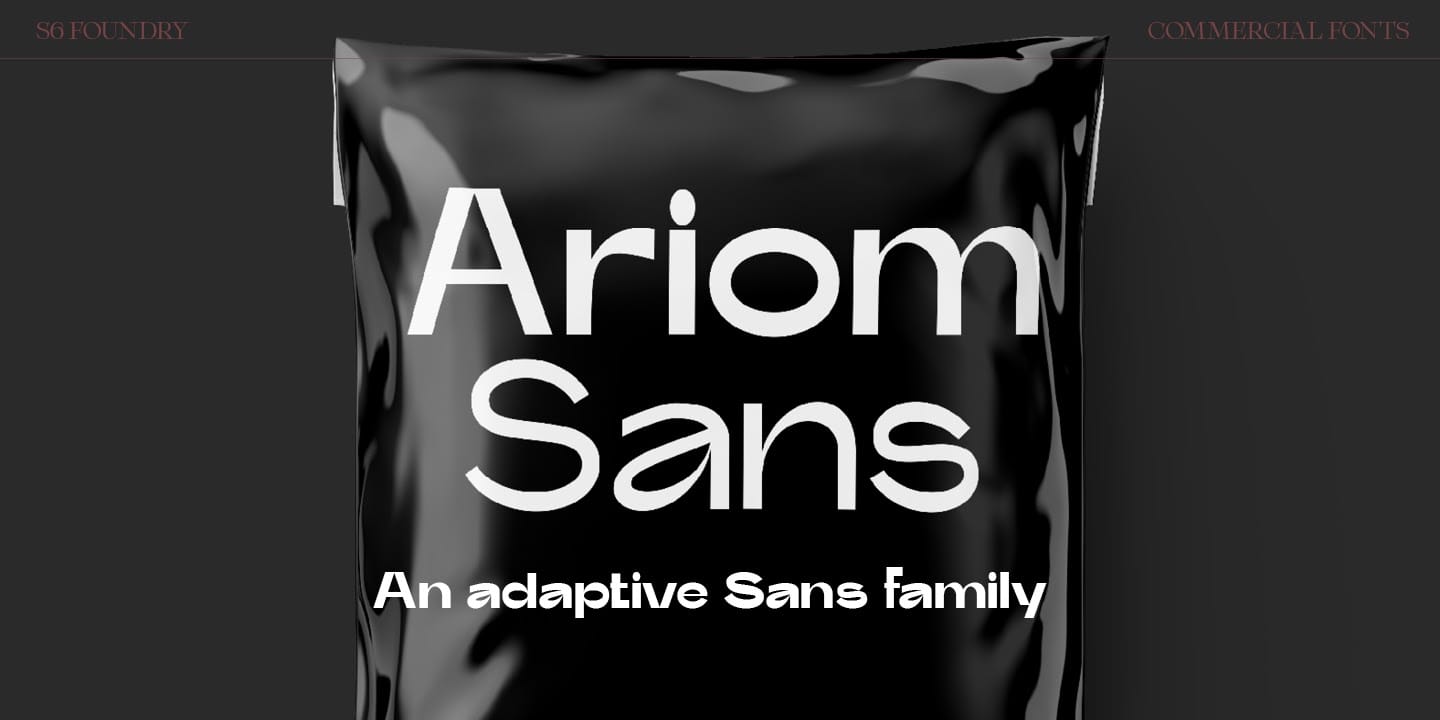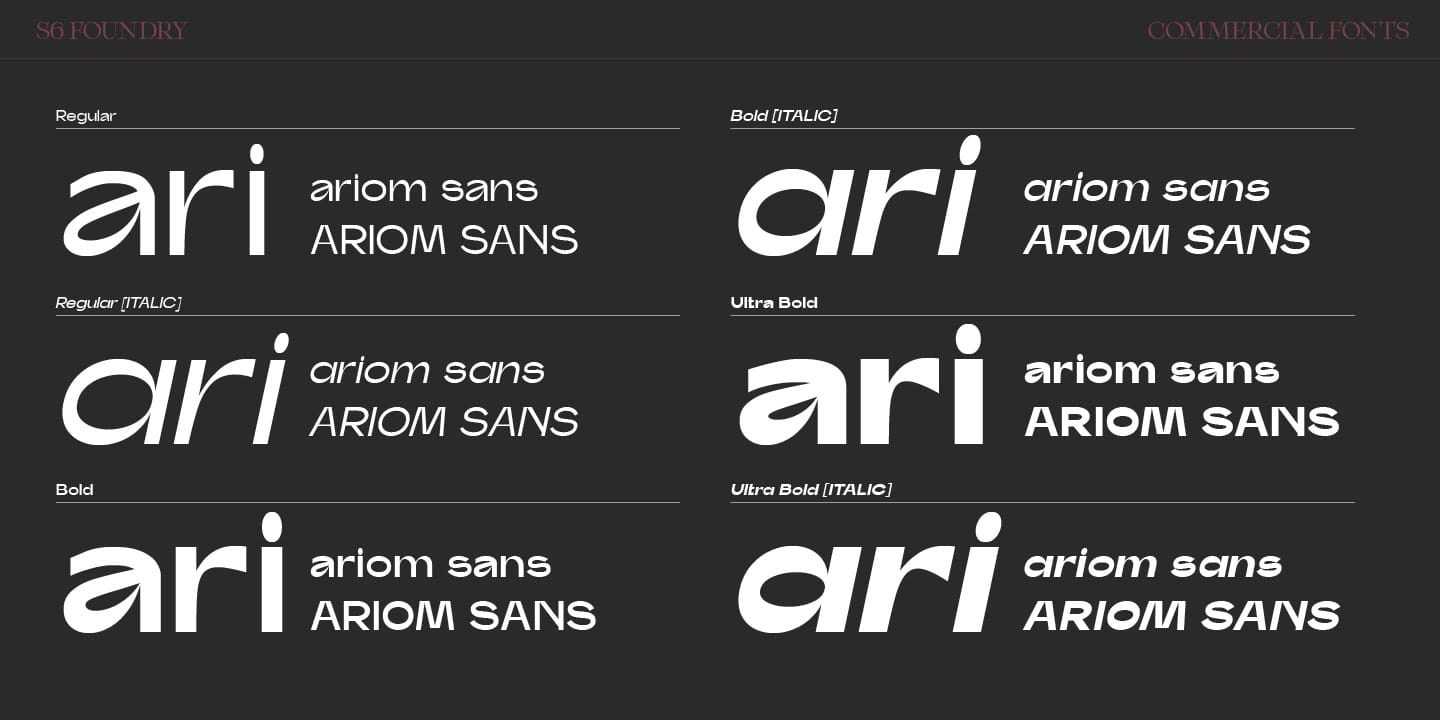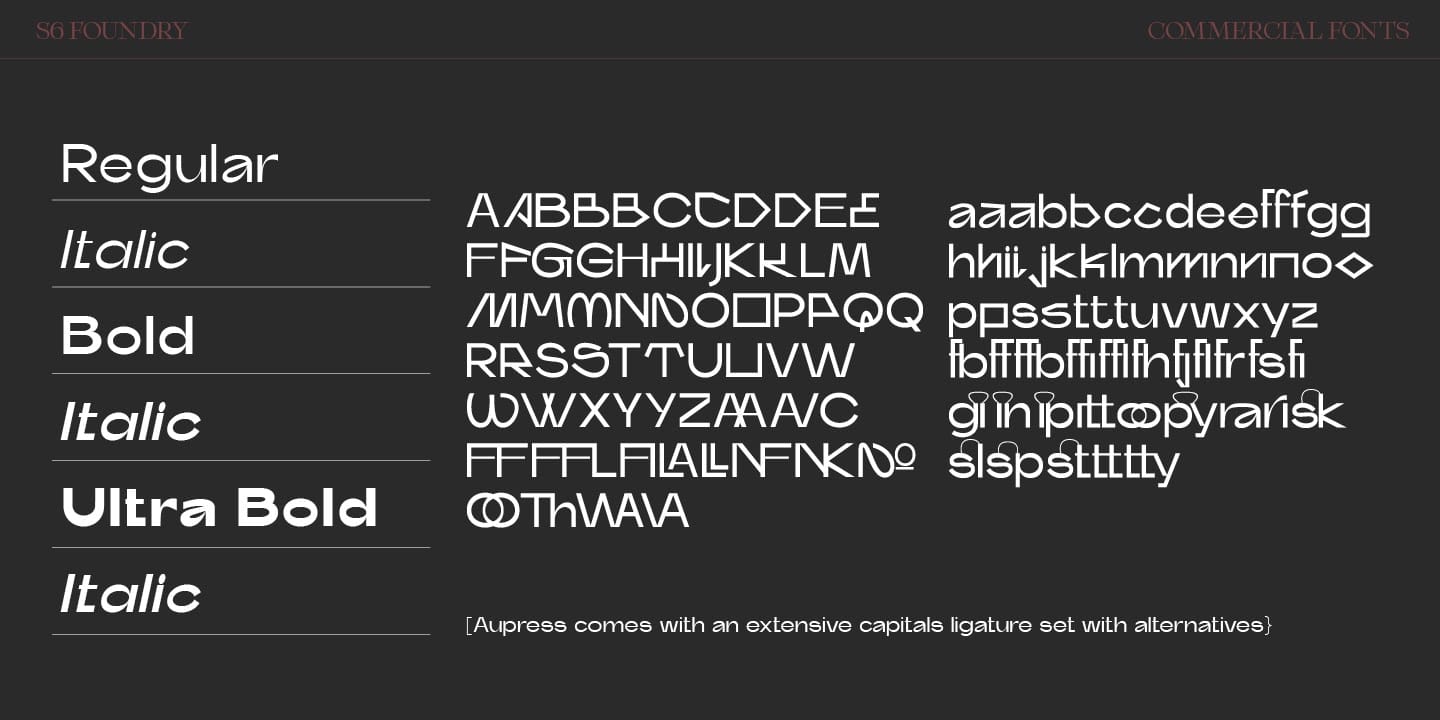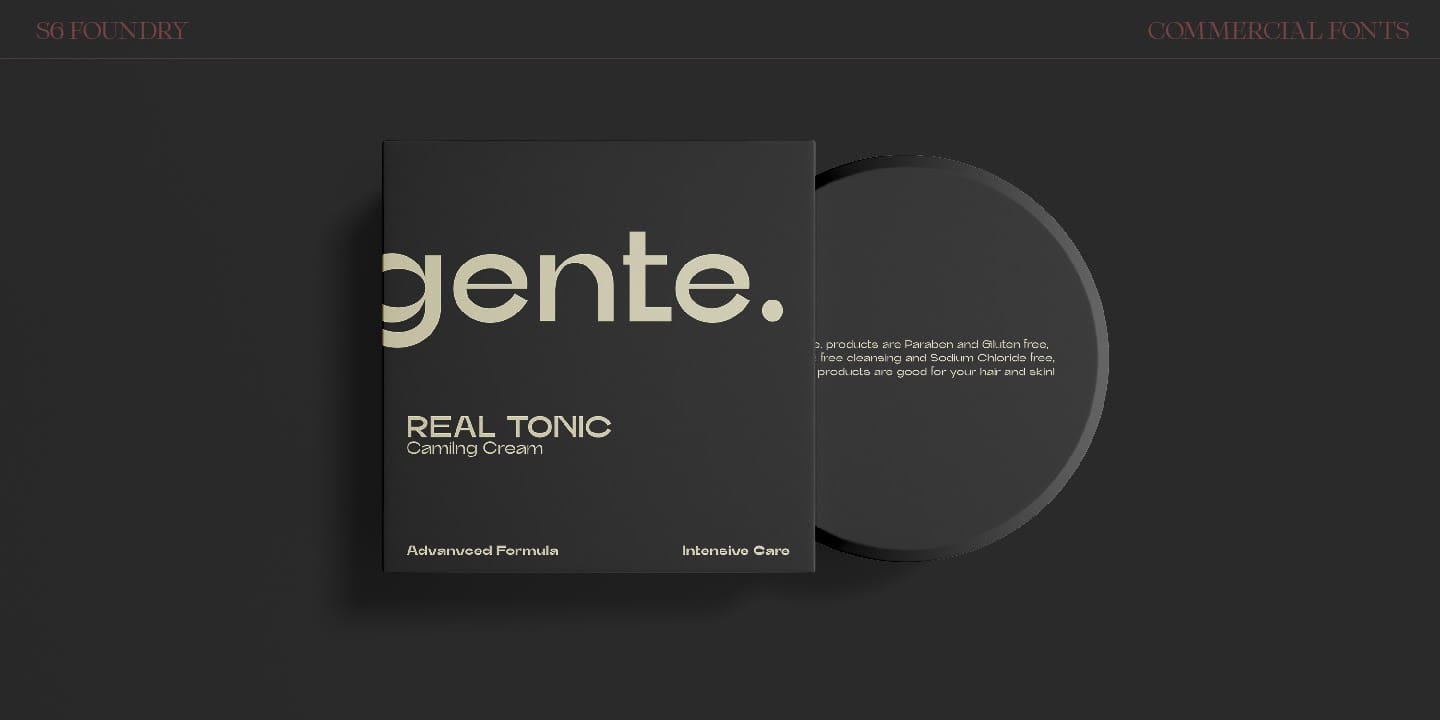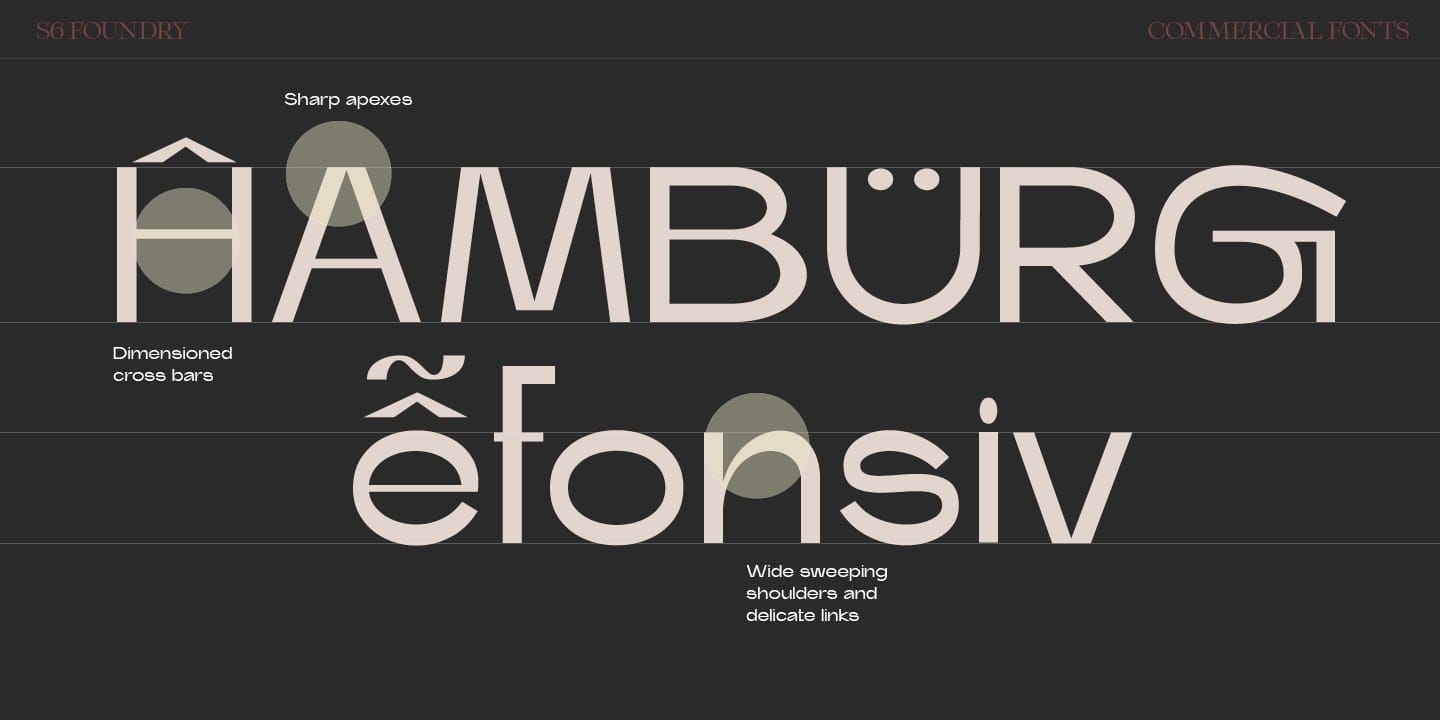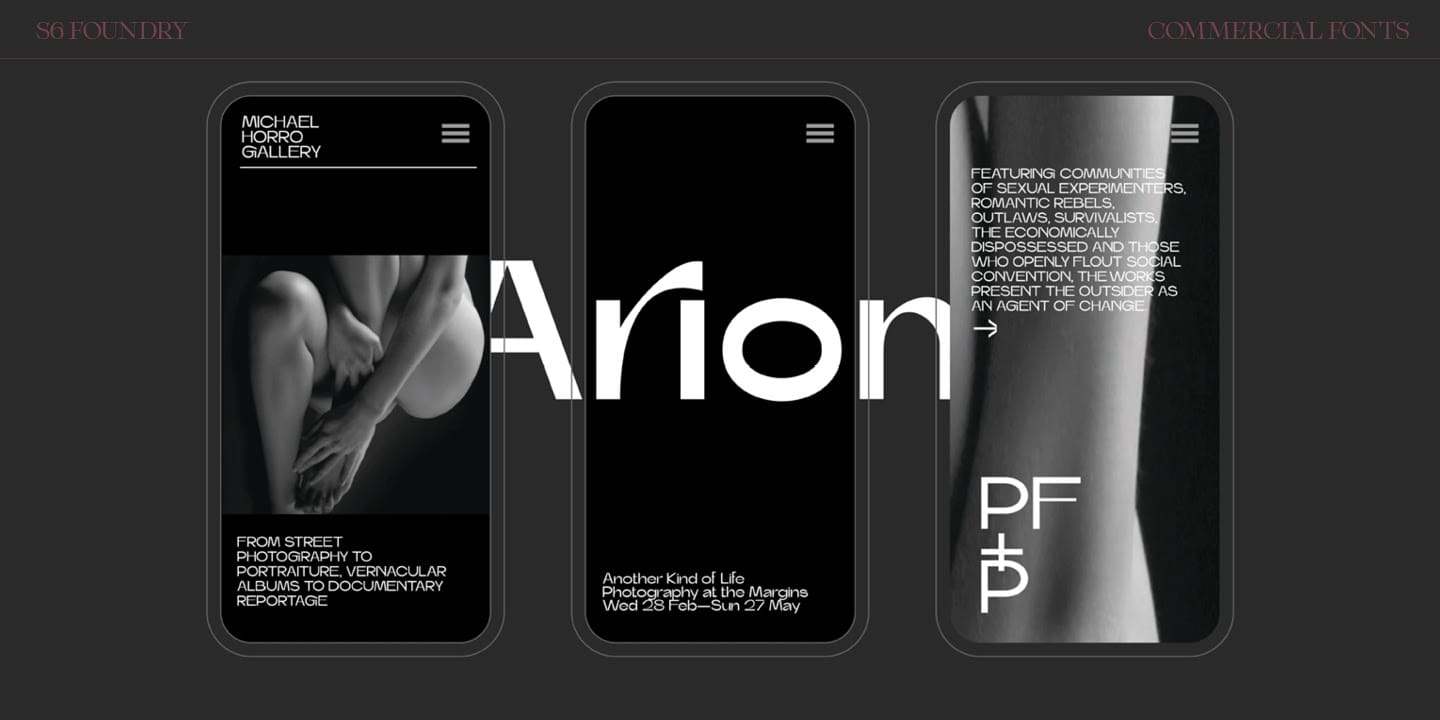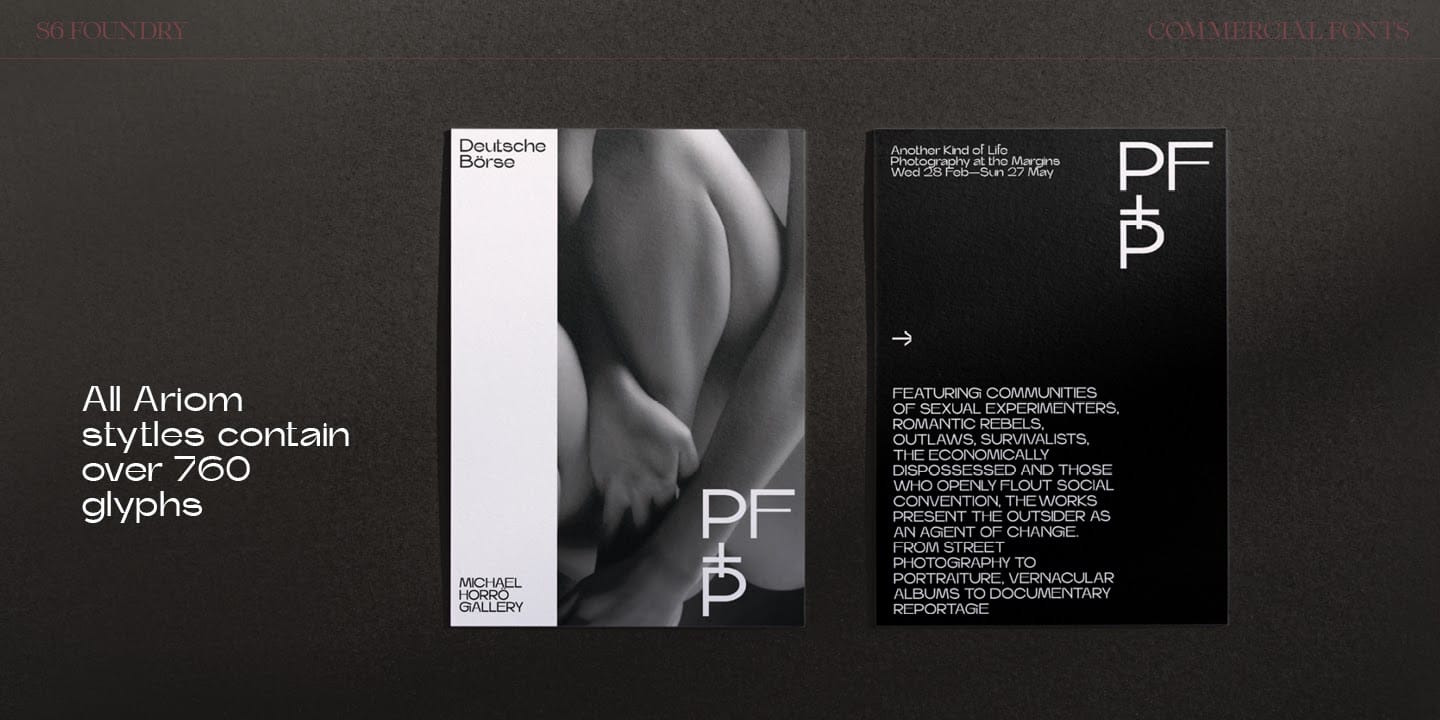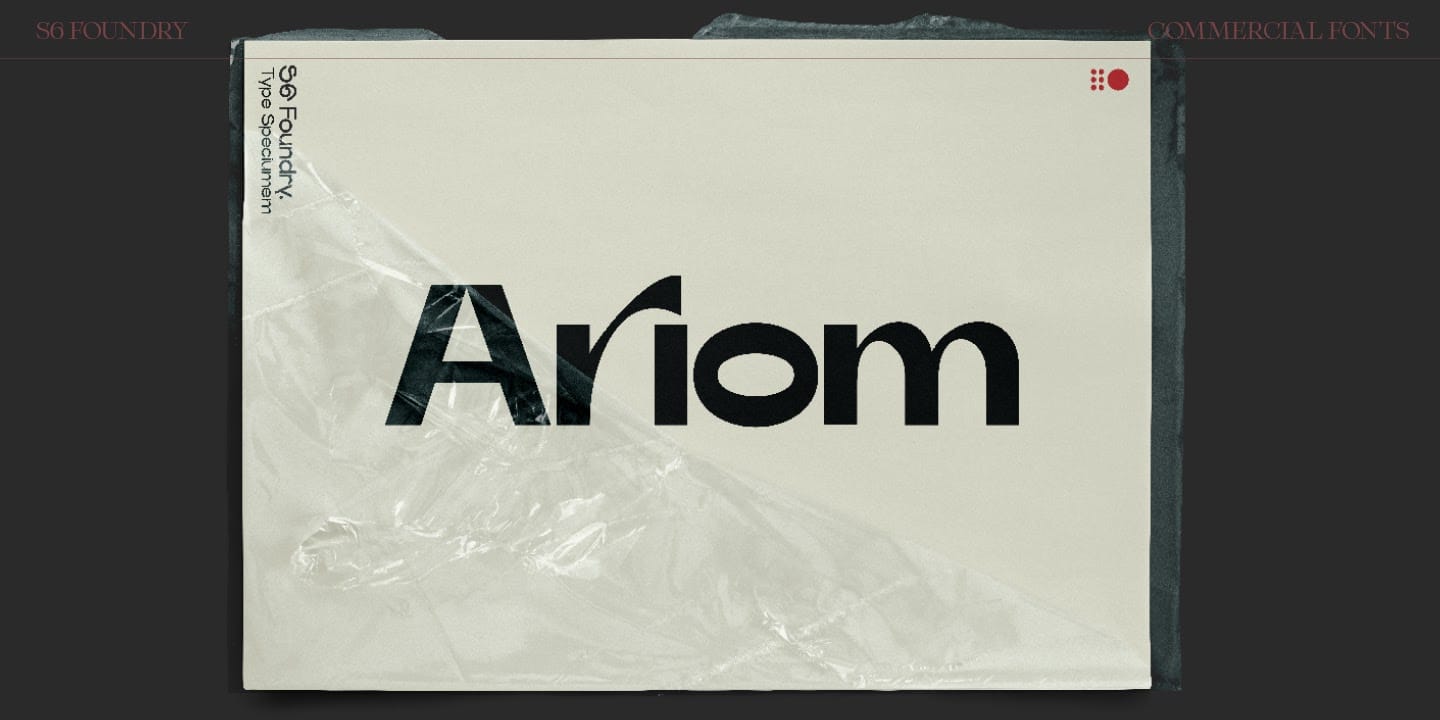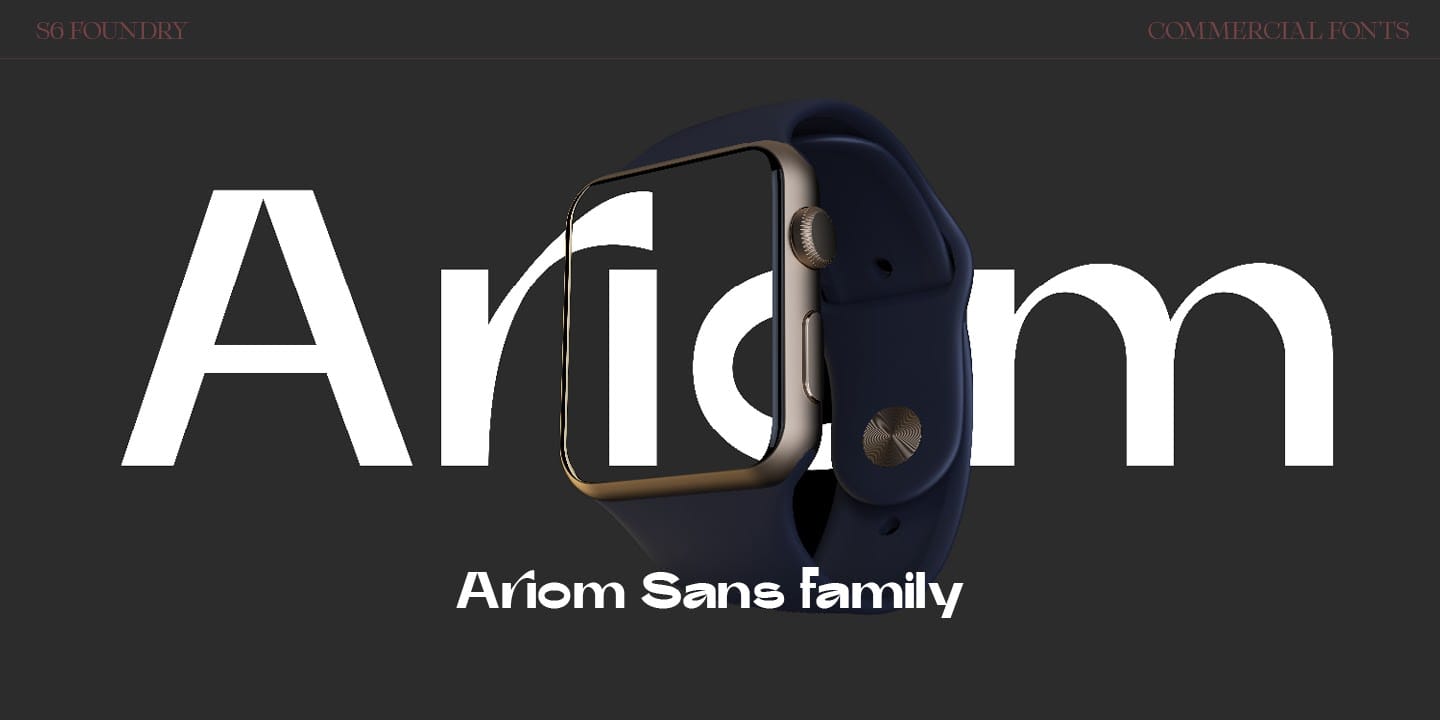
Ariom là một bộ font chữ sans-serif mới, hình học, được lấy cảm hứng từ những kiểu chữ mang tính biểu tượng. Ariom có giá trị x-height lớn, các dạng chữ hình học, các cạnh sắc nét và độ tương phản nét mạnh mẽ như các font chữ xưa cũ từ thế kỷ 20.
Kiểu chữ này rất linh hoạt và có thể được sử dụng thành công trên tạp chí, áp phích, thương hiệu, trang web, tiêu đề, bản in khổ lớn, bản sắc thương hiệu, phương tiện truyền thông xã hội, quảng cáo, thiết kế biên tập, áp phích.
Ariom Sans Family chứa hơn 40 glyph thay thế và hơn 50 chữ ghép ở mỗi kiểu.
Bộ font hỗ trợ đa ngôn ngữ phương Tây, Trung, Đông Nam, Nam Mỹ, Châu Đại Dương, Liên Phi, Việt Nam và Sámi.